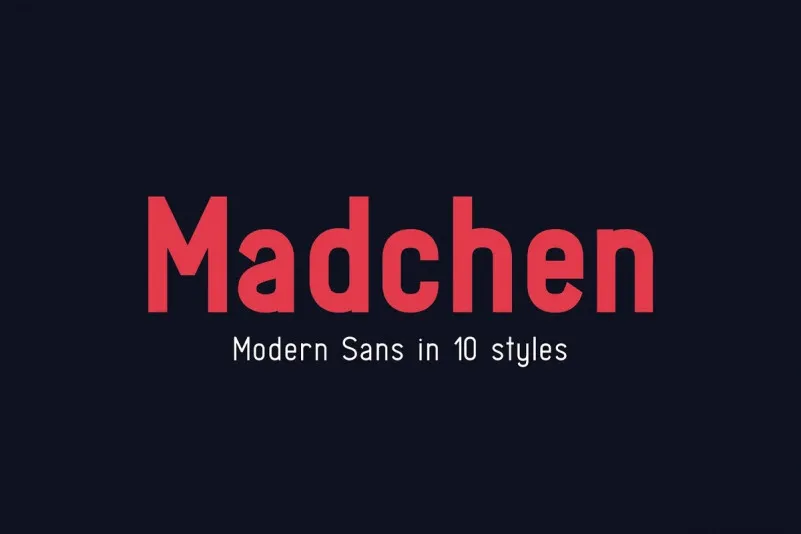
A Madchen Font é uma família de tipo geométrica com uma dose sutil de formalidade, que contém dez variantes, desde a fina até o preto e os versões itálicas da fina ao preto. Essa elegante serifada sans-serif é ideal para aplicações digitais como o design para tela, editorial e publicações, logotipos, campanhas de marketing e identidades corporativas. Além disso, a Madchen oferece uma ampla gama de suporte linguístico incluindo Latin Extendido. Ideal tanto para designers profissionais quanto para aqueles que querem adicionar um toque sofisticado às suas criações digitais sem se preocupar em esgotar o armário de tipos de fonte, a Madchen Font é uma excelente escolha. Seja você criando material editorial, estilizando materiais de marketing ou simplesmente buscando tornar seu design mais profissional e elegante, essa família de typeface vem para você.